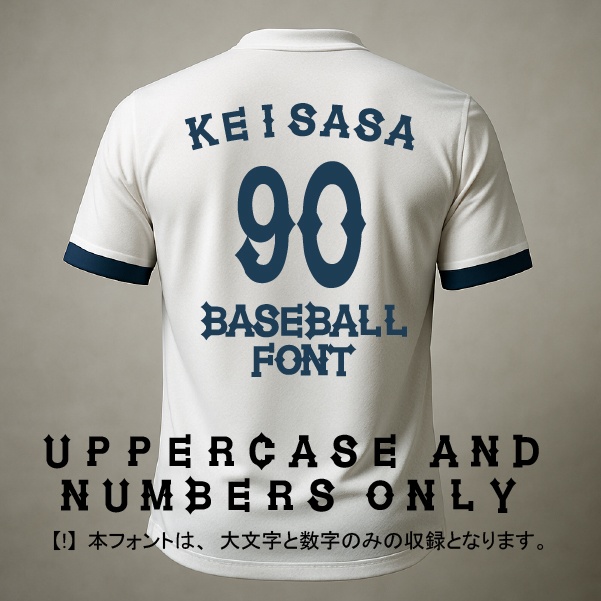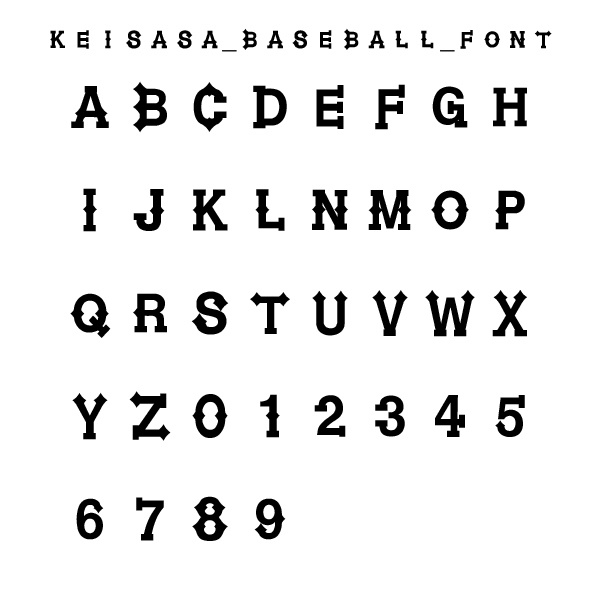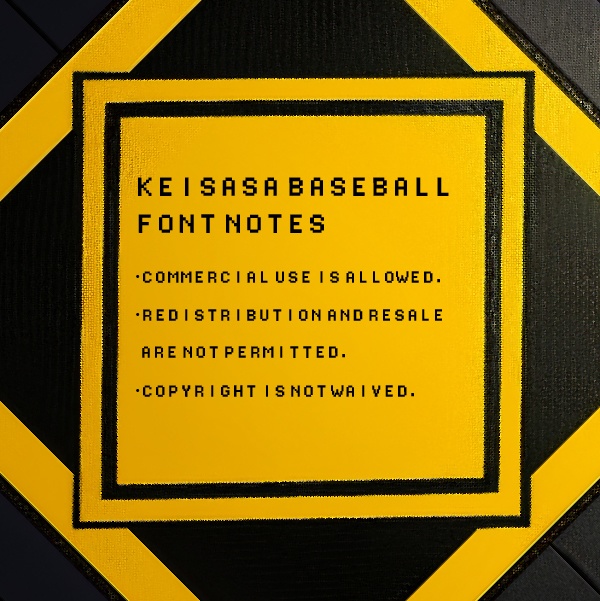
keisasa baseball font︱野球ユニフォーム風ヴィンテージ・ボールド
収録文字:A–Z(大文字)、0–9 フォーマット:TTF 商用利用:可 再配布・転売:不可 制作:sasasasaya / ksuke sasaki フォントの力強いデザインを活かして、商品の魅力をしっかりと伝えつつ、仕様(大文字・数字のみ)をスムーズに織り込んだ説明文を作成したよ。 日本語説明文(中規模) 伝統的なスタジアムの熱気を、その手に。 「keisasa_baseball_font」は、ヴィンテージのベースボールユニフォームやカレッジスウェットから着想を得た、クラシックかつ力強いアスレチック・フォントです。 独特の鋭いセリフ(装飾)が、スポーツウェア特有のタフさと伝統的な風格を演出します。 チームロゴのデザイン、背番号のシミュレーション、アパレルプリント、ポスターのタイトルなど、インパクトを重視するクリエイティブに最適です。 【収録内容とご注意】 本フォントは、デザインの純粋さを保つため、「英大文字(A-Z)」と「数字(0-9)」のみを収録した特化型フォントです。小文字や記号は含まれておりませんので、あらかじめご了承ください。 English Description (Medium length) Bring the classic stadium energy to your design. "keisasa_baseball_font" is a powerful athletic font inspired by vintage baseball jerseys and heritage collegiate styles. Its unique, sharp serifs deliver a tough, authentic look that captures the spirit of traditional sports apparel. This font is perfect for team logos, jersey numbers, apparel prints, and bold headlines that demand attention. [Important Specifications] To maintain its bold aesthetic, this font includes UPPERCASE letters (A-Z) and NUMBERS (0-9) only. Please note that lowercase letters, symbols, and special characters are not included in this set.